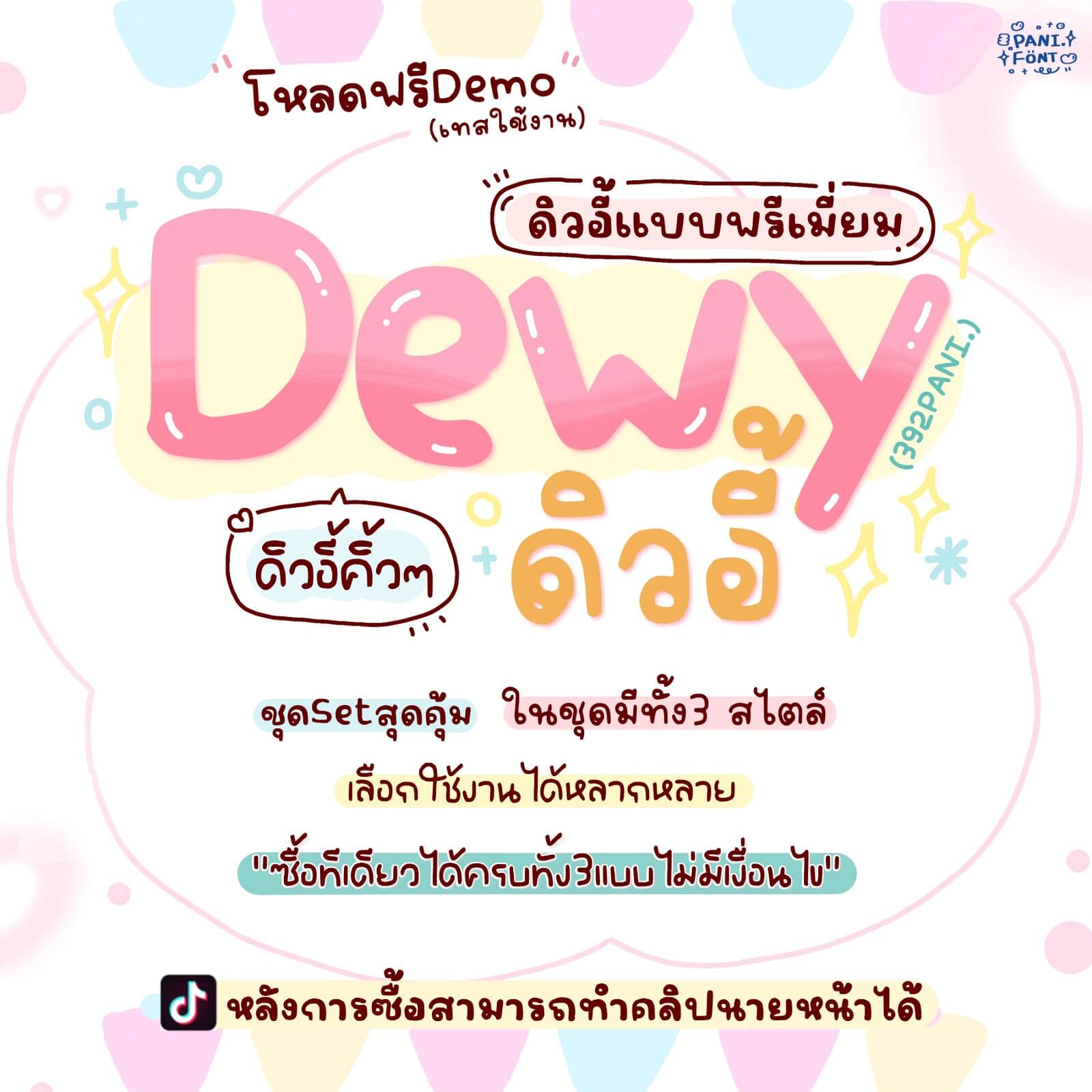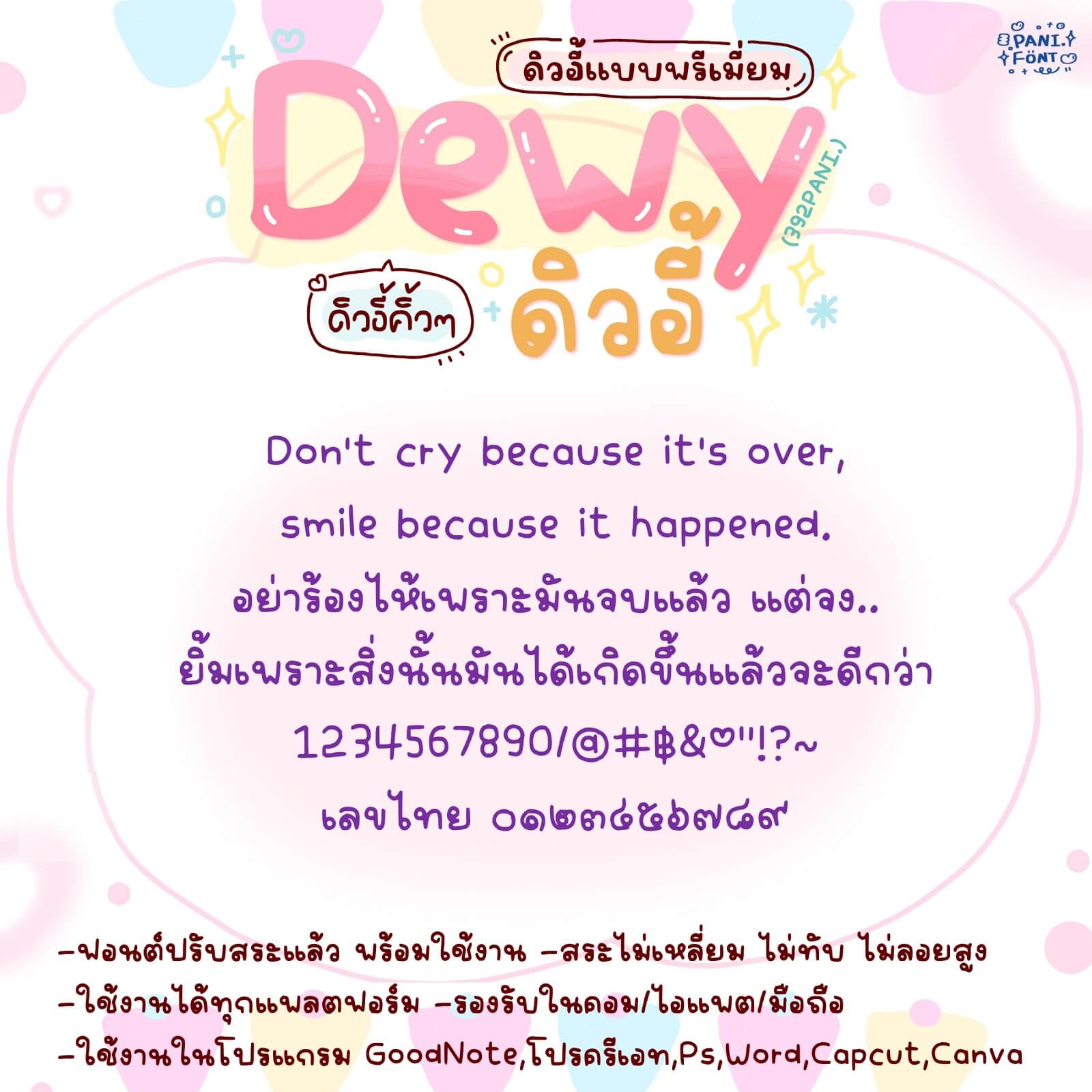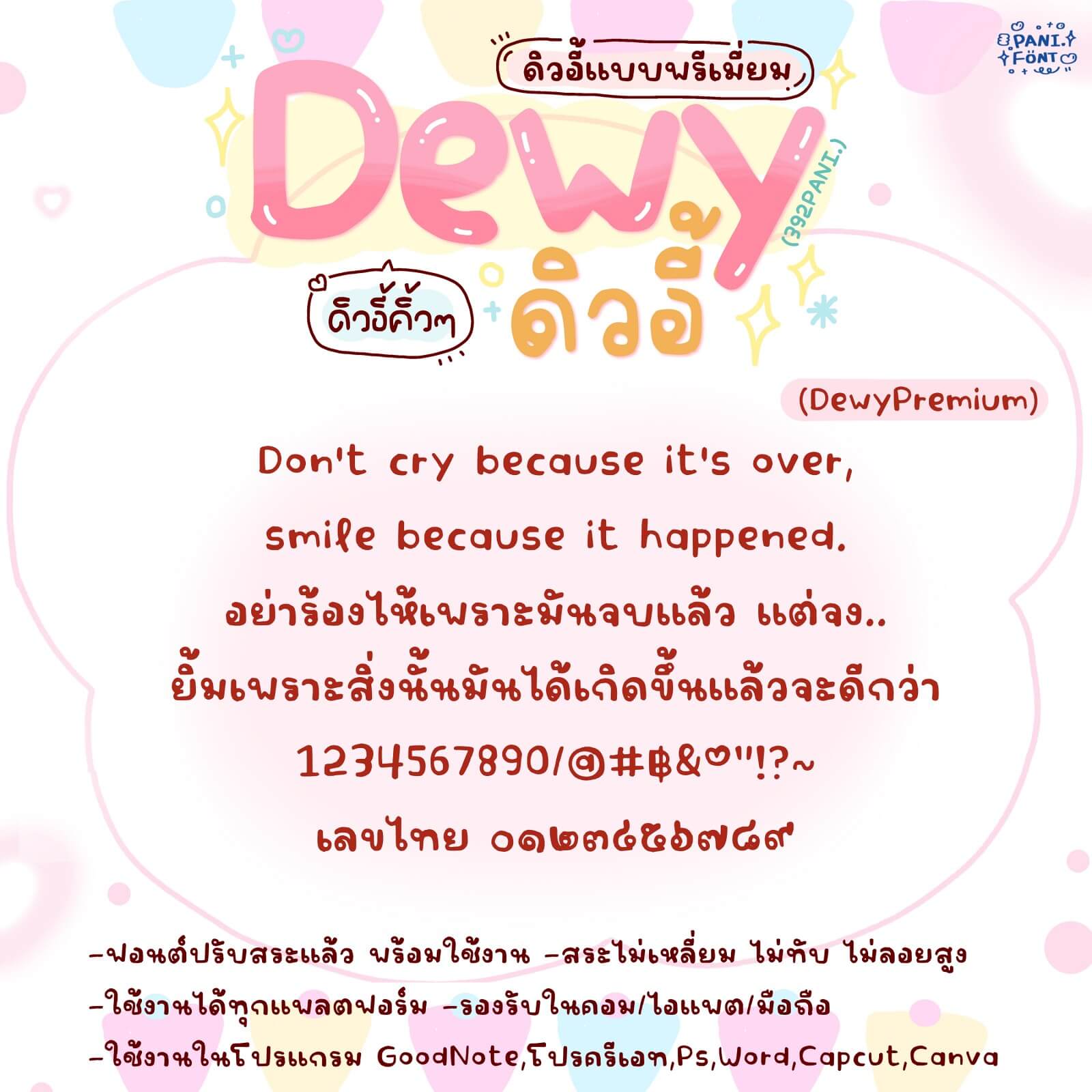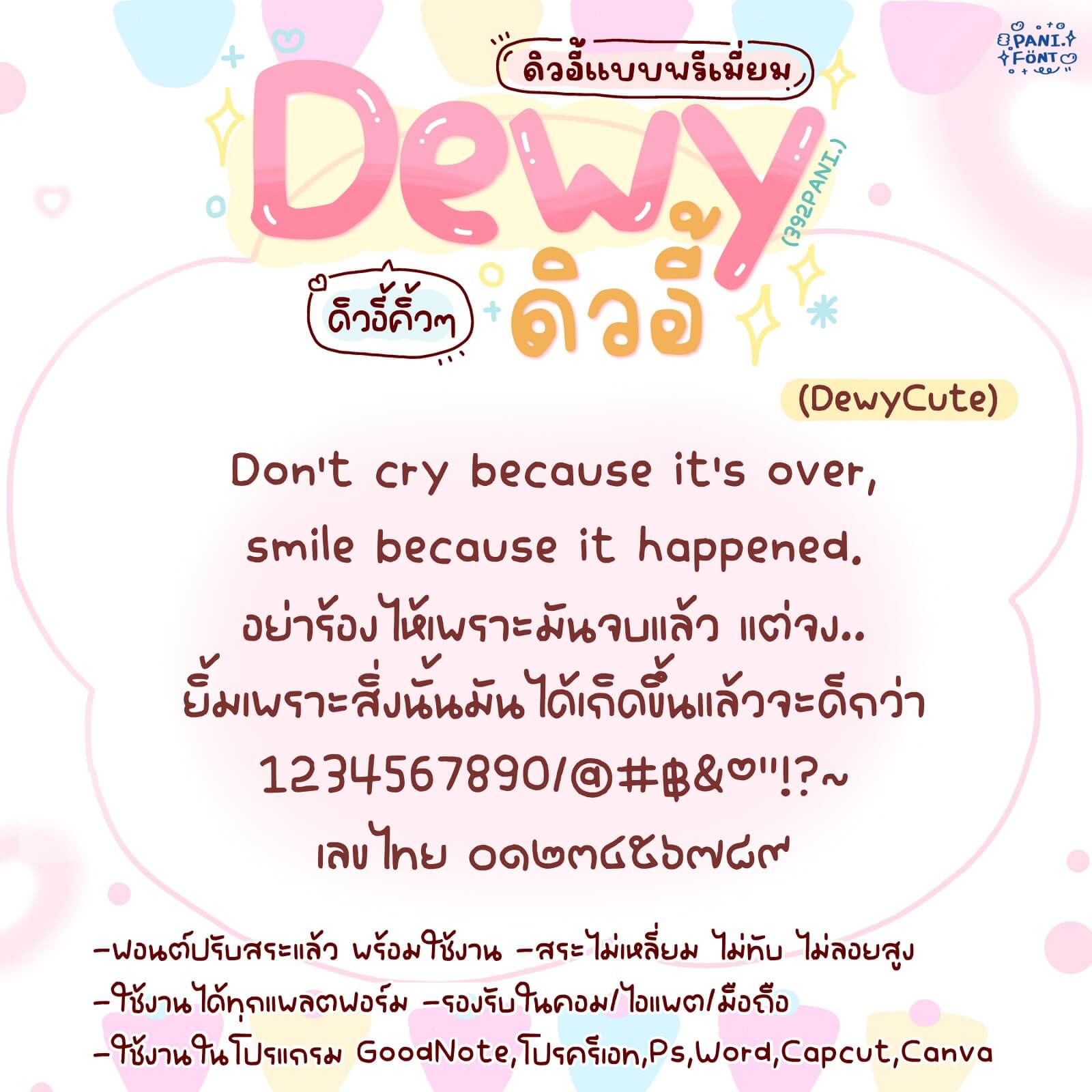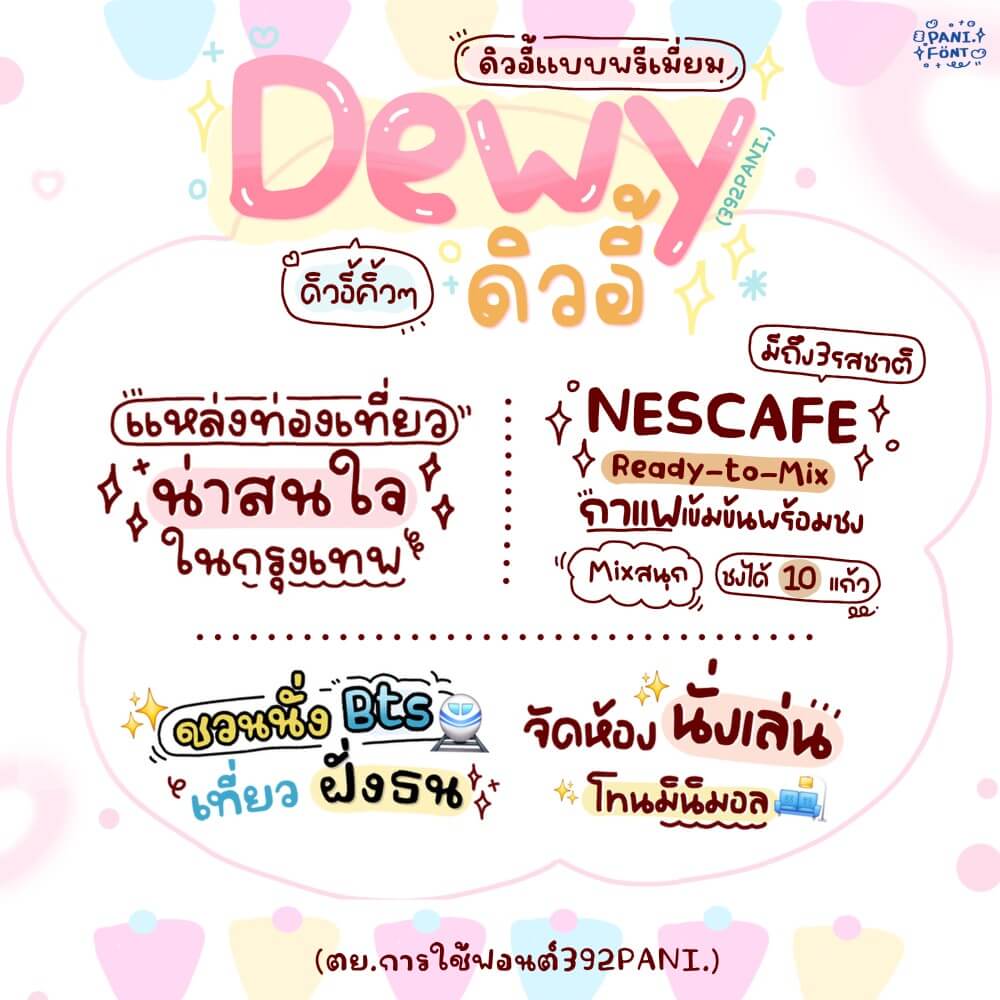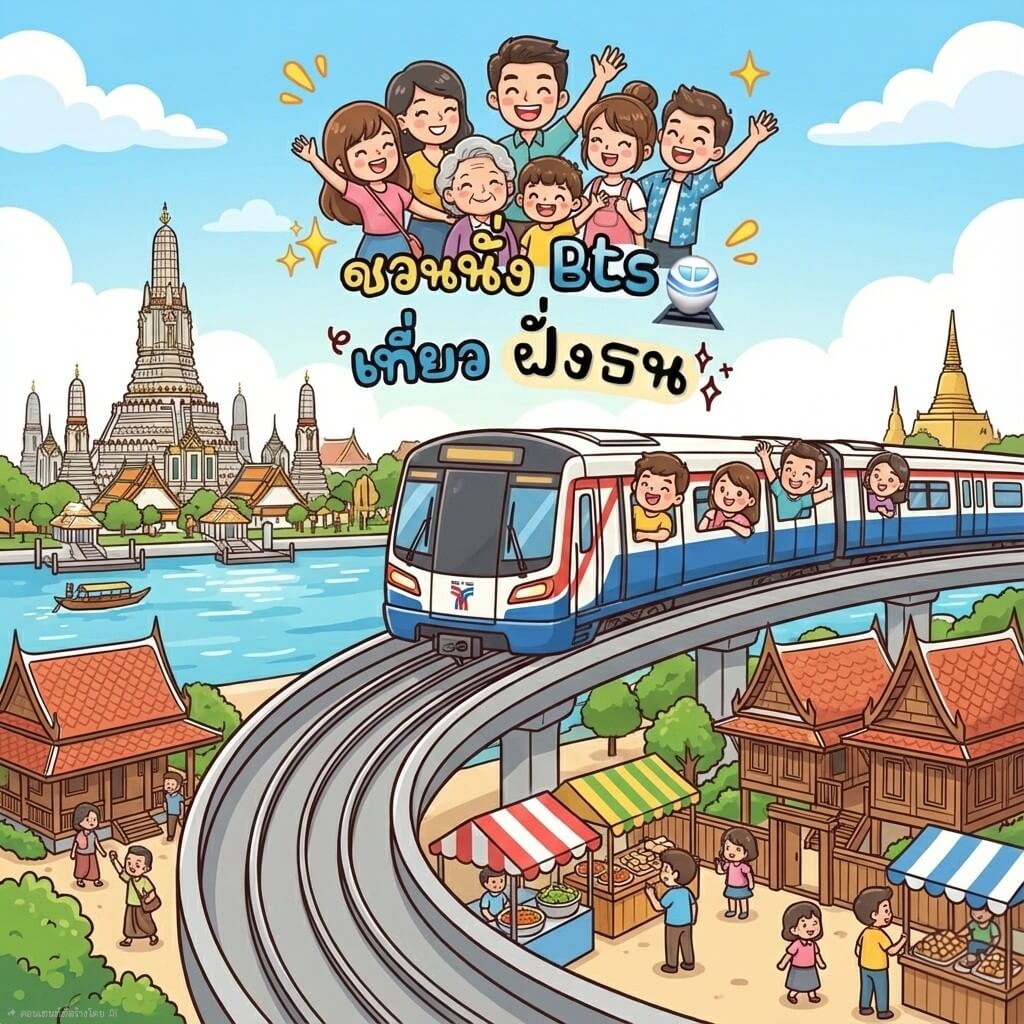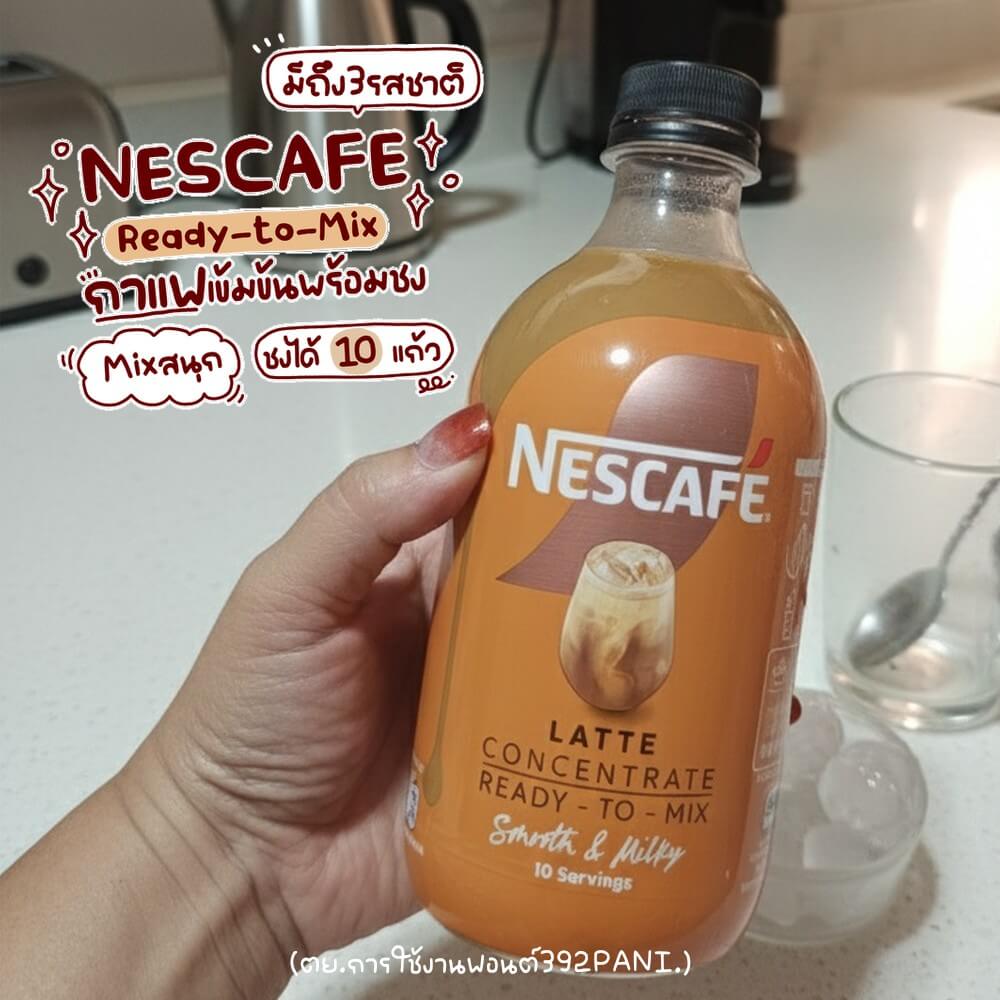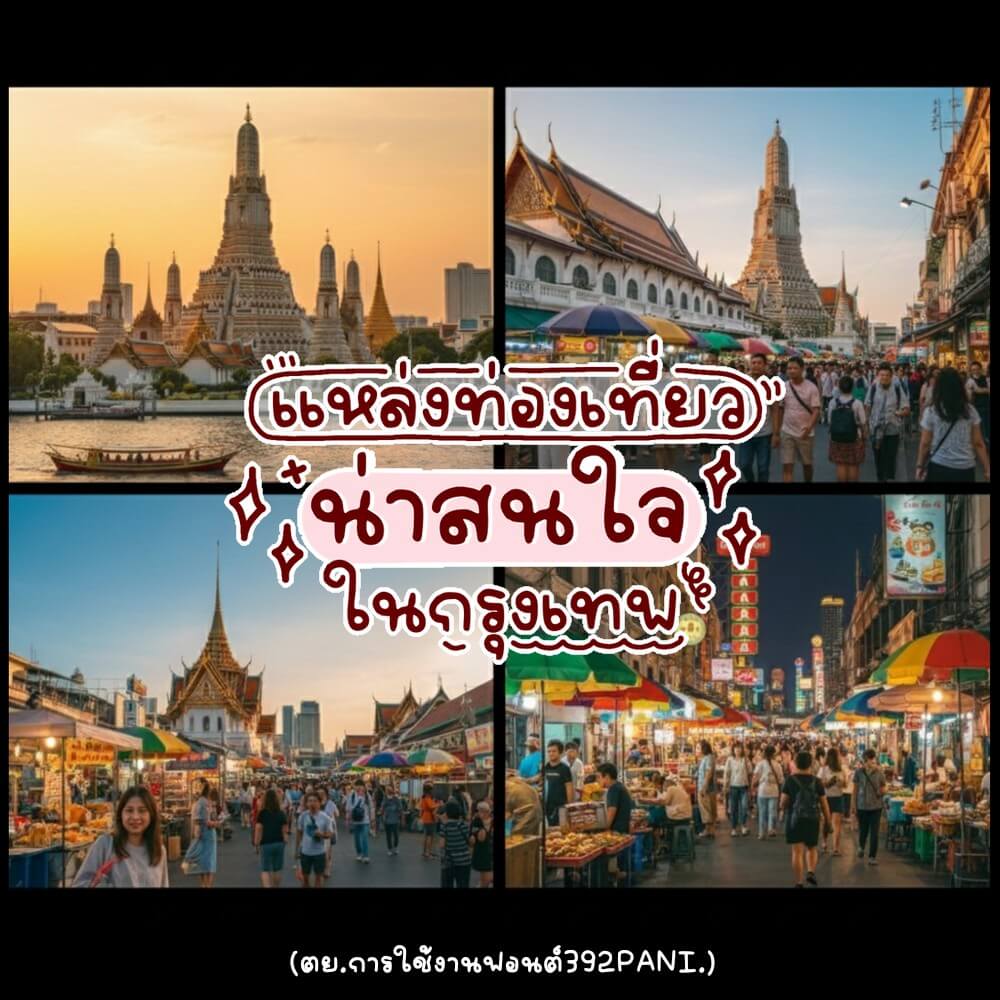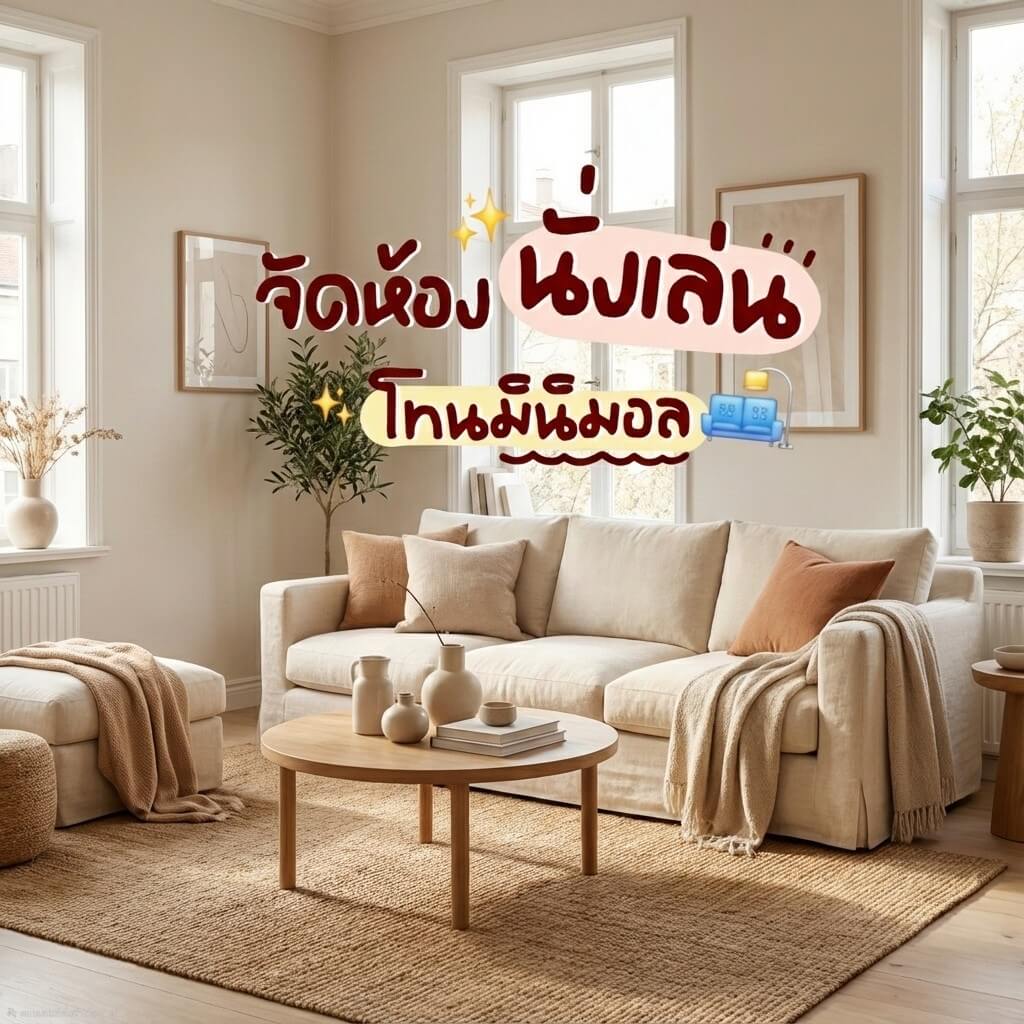
392PANI.ดิวอี้
ฟอนต์ 392PANI.ดิวอี้ – ชุดนี้ครบแบบคุ้มๆ ได้ทั้ง 3 สไตล์ ใช้งานได้หลากหลายสุดๆ ครบจบในชุด จัดรอบเดียว ได้หมดนี่เลยค่ะ
แต่งแบบแนวมินิมัล เท่ๆ คูลๆ